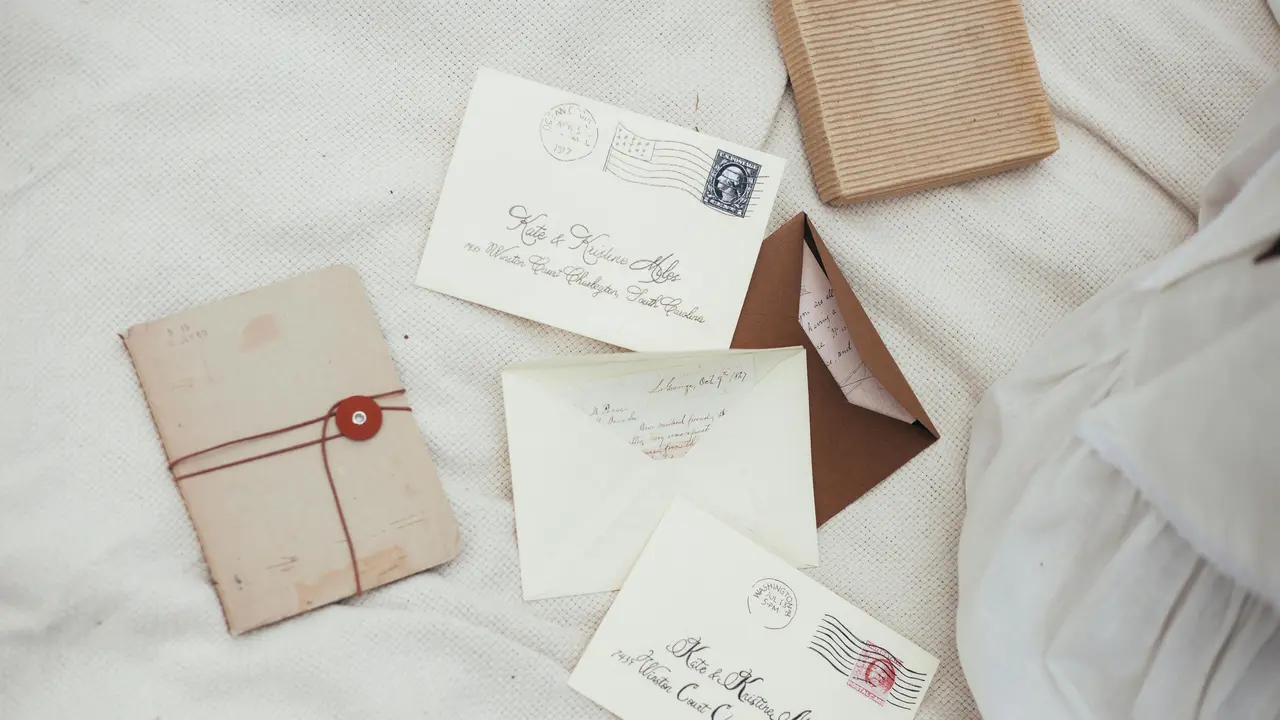
Liputan6.com, Jakarta Pemilihan font nama yang tepat menjadi salah satu aspek penting dalam menciptakan identitas visual yang menarik, baik untuk keperluan desain grafis maupun media sosial. Setiap font nama memiliki karakteristik unik yang dapat mempengaruhi persepsi audiens terhadap pesan yang ingin disampaikan. Dengan memahami berbagai jenis font nama yang tersedia, Anda dapat memaksimalkan dampak visual dari konten yang dibuat.
Di era digital seperti sekarang, penggunaan font nama yang tepat tidak hanya sebatas pada aspek estetika, tetapi juga berkaitan erat dengan tingkat keterbacaan dan profesionalitas sebuah desain. Beragam pilihan font nama yang tersedia memungkinkan desainer dan pengguna untuk mengekspresikan kreativitas mereka sekaligus mempertahankan kejelasan pesan yang ingin disampaikan.
Artikel ini akan membahas 16 jenis font nama populer yang dapat Anda gunakan untuk berbagai keperluan desain. Mulai dari font nama klasik hingga modern, formal hingga casual, setiap jenis memiliki karakteristik dan fungsi spesifiknya masing-masing. Mari kita eksplorasi lebih dalam tentang ragam font nama yang dapat meningkatkan kualitas desain Anda.
Lebih jelasnya, berikut ini telah Liputan6.com rangkum dari berbagai sumber jenis-jenis font nama yang bagus untuk desain grafis dan media social, pada Selasa (19/11/2024).
Bab 1: Font Klasik yang Tak Lekang oleh Waktu
1. Serif: Elegansi Klasik dalam Setiap Goresan
Font Serif merupakan salah satu jenis font tertua yang masih relevan hingga saat ini. Karakteristik utamanya adalah adanya garis kecil (counter stroke atau serif bracketed) di setiap ujung hurufnya, yang berasal dari tradisi penulisan bangsa Romawi kuno menggunakan kuas.
Kehadiran Serif di dunia tipografi modern tidak lepas dari sejarah panjangnya yang dimulai pada abad ke-15. Font ini dianggap sebagai pilihan paling formal dan memiliki tingkat keterbacaan yang sangat baik berkat bantuan counter stroke-nya. Beberapa variasi populer dari font Serif meliputi Old Style, Neo-Klasik, dan Transisional, dengan contoh seperti Times New Roman, Georgia, dan Cambria.
2. Sans Serif: Modernitas dalam Kesederhanaan
Sans Serif, yang dalam bahasa Perancis berarti "tanpa serif", hadir sebagai revolusi dalam dunia tipografi. Diciptakan oleh William Caslon IV pada tahun 1816, kemunculannya sempat dianggap kontroversial karena mendobrak tradisi tipografi Eropa saat itu.
Karakteristik utama Sans Serif adalah ketiadaan garis kecil di ujung hurufnya, memberikan kesan modern, sederhana, dan efisien. Tidak mengherankan jika banyak perusahaan teknologi dan startup modern seperti Google, Spotify, dan Netflix memilih menggunakan font jenis ini untuk logo mereka. Arial, Calibri, dan Futura adalah beberapa contoh populer dari keluarga Sans Serif.
3. Slab Serif: Kekuatan dalam Ketebalan
Slab Serif muncul sebagai jawaban atas kebutuhan font yang dapat terbaca dari jarak jauh pada abad ke-19. Karakteristiknya yang tebal dan berbentuk seperti blok membuatnya ideal untuk penggunaan pada media seperti billboard, poster, dan pamflet.
Font ini menghadirkan sentuhan vintage dalam desain modern, dengan beberapa variasi seperti Antique, Clarendon, Typewriter, dan Geometric. Rockwell, Courier, dan Clarendon adalah contoh populer dari keluarga Slab Serif yang masih banyak digunakan hingga saat ini.
Bab 2: Font Artistik dan Dekoratif
4. Script: Keanggunan Tulisan Tangan
Script membawa kesan personal dan elegan dengan karakteristik tulisan tegak bersambungnya. Font ini ideal untuk desain yang membutuhkan sentuhan personal dan artistik, meskipun penggunaannya terbatas pada tulisan singkat karena tingkat keterbacaannya yang lebih rendah untuk teks panjang.
Penggunaan Script memerlukan pertimbangan khusus, terutama dalam hal kombinasi huruf kapital dan kecil untuk mempertahankan kesinambungan tulisan. Bromello, Brush Script MT, dan Palace Script MT adalah beberapa contoh font Script yang populer digunakan dalam desain modern.
5. Handwritten: Sentuhan Personal dalam Desain
Font Handwritten membawa dimensi baru dalam dunia desain dengan karakteristiknya yang menyerupai tulisan tangan asli manusia. Keunikan font ini terletak pada kemampuannya menciptakan koneksi personal dengan audiens, seolah-olah mereka membaca pesan yang ditulis langsung oleh seseorang.
Meskipun penggunaannya terbatas seperti Script, Handwritten memiliki tempat khusus dalam dunia desain, terutama untuk sampul buku, poster, dan logo yang membutuhkan sentuhan personal. Font seperti Courgette, Cookie, dan Neucha adalah contoh populer yang sering digunakan untuk memberikan kesan kreatif dan unik dalam sebuah desain.
6. Display: Keindahan dalam Ornamen